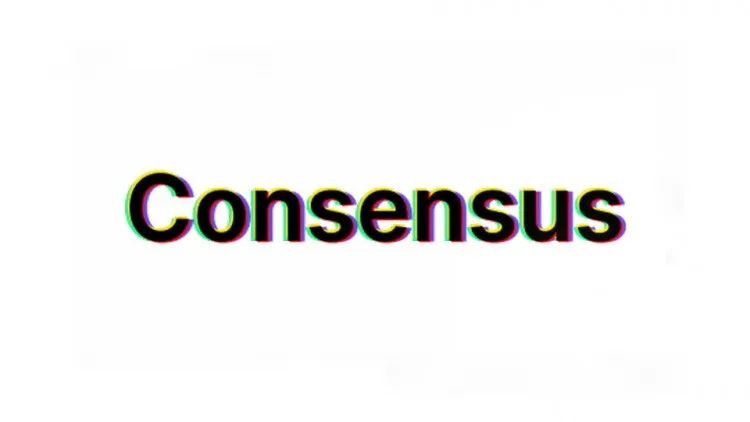
A Consensus Font é uma fonte sans-serif que foi projetada para atender às necessidades do branding corporativo moderno, das propagandas de copywriting até qualquer aplicação digital. Suas 7 pesos (do fininho ao grosso) permitem adaptabilidade e flexibilidade ao criar um design único e profissional. Em um mundo em constante evolução, a Consensus oferece uma solução clara e inovadora para estilos modernos de marca. Essa fonte é perfeita para quem busca uma aparência simples e futurista sem perder o poder da informação. Combinada com cores vibrantes e imagens criativas, essa fonte pode transformar qualquer layout em um destaque no digital. Seja para criação de logos ou desenvolvimento de websites, a Consensus é uma escolha inteligente. Além disso, sua simplicidade não compromete a legibilidade e facilidade de uso do texto, tornando-a ideal tanto para títulos quanto para o corpo da página. Combinada com as cores e imagens certas, essa fonte pode transformar qualquer visual em um design sólido e moderno.